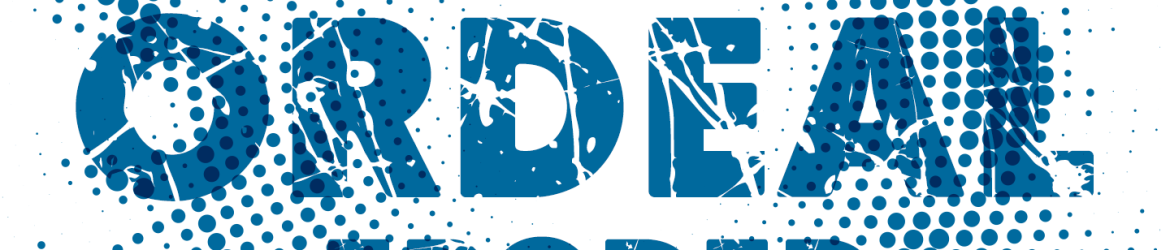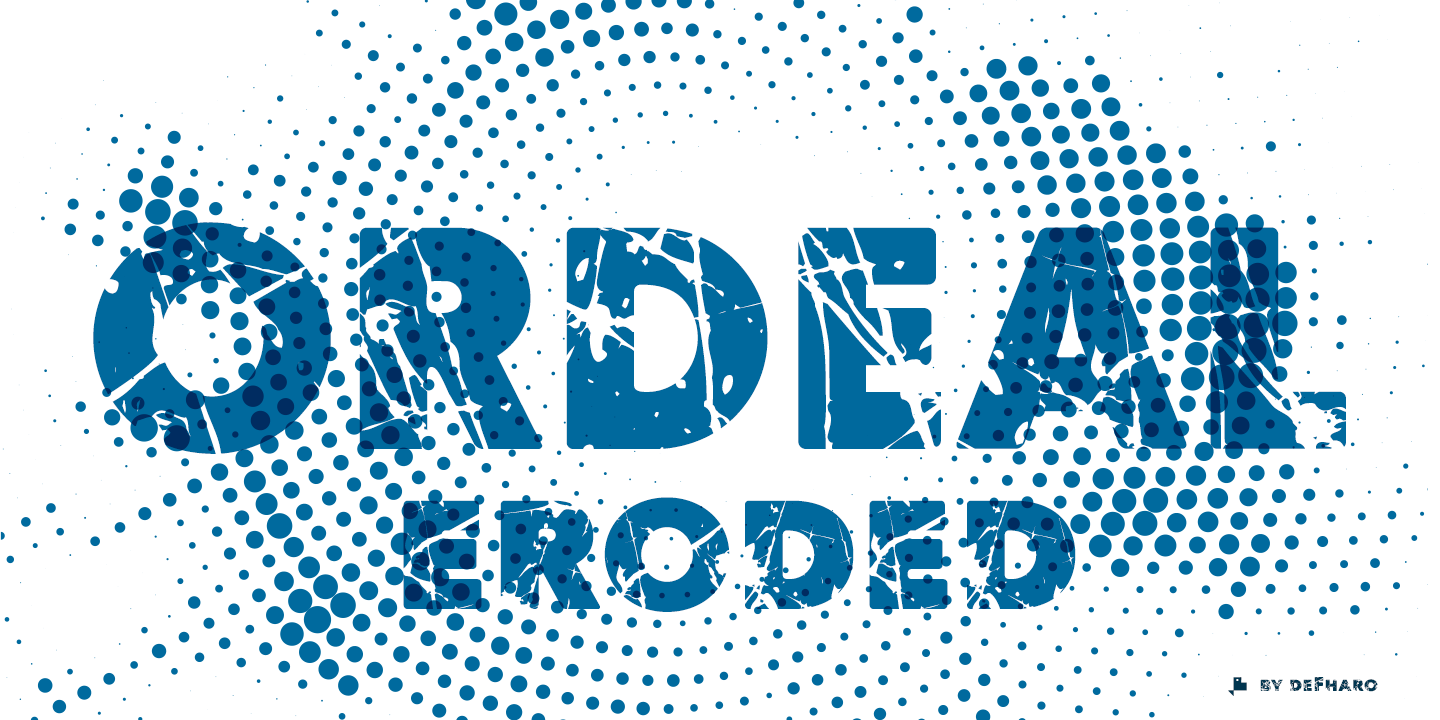
ORDEAL eroded Font – Fonte Grátis
ORDEAL eroded Font
A Ordeal Eroded é uma fonte Display que resulta do pesadelo de passar por calvarios a uma família de tipografia sans serif. Ela se baseia num Paloseco muito escuro, mas transformado em um tipo de fonte grande e visível. Nessa fonte-display, o sofrimento tipográfico é capturado de maneira única e repleta de inocência. Ideal para ambientes que precisam de uma sensação poderosa e dramática, esta fonte combina a força arquitetônica do sans serif com um grau singular de vulnerabilidade emocional, criando uma intersecção entre drama e tranquilidade. Com certeza é uma escolha perfeita para aqueles projetos que exigem uma presença forte, mas não se limitam a ser sólidas e imutáveis. É uma fonte para quem busca algo mais que apenas uma ferramenta de escrita direta; ela oferece uma oportunidade de explorar o poder do design gráfico em um nível muito além das palavras.